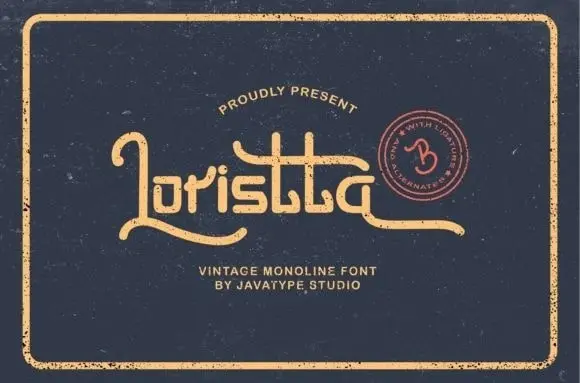
Loristta Script Font – Download Grátis
Loristta Script é uma fonte tipográfica script monoline que oferece inúmeras alternativas para caracteres decorativos. Seu design único permite criar escrita autêntica e atraente, ideal tanto para projetos pessoais quanto corporativos. Com um conjunto variado de letras alternativas, você pode personalizar cada palavra em seu projeto para destacá-la com estilo. Loristta Script é uma fonte versátil que inclui caracteres delicados e clássicos, tornando-a a escolha perfeita para quem busca dar vida à ideias criativas. Sua elegância irradia de qualquer página onde é usada, tornando Loristta Script uma opção irresistível para projetos gráficos. Engaje-se com sua personalidade única e apaixone-se pelo mundo do design visual com Loristta Script, uma fonte script perfeita para quem valoriza tanto a criatividade quanto o bom gosto.